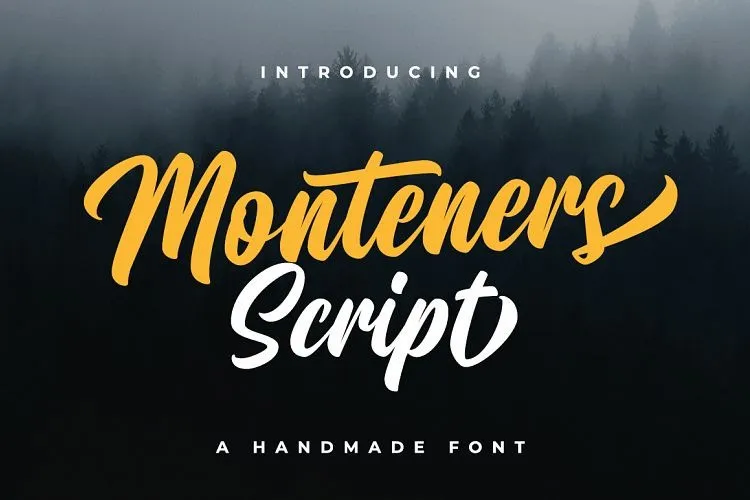
Monteners Script Font – Download Grátis
Estou aqui uma nova fonte Script Bold Retro inspirada em escrita manual, com influência moderna do caligrafismo. Introduzimos a Monteners Font — uma elegante e bonita tipografia script desenvolvida pelo Studio Suby. Esta fonte é perfeita para qualquer projeto gráfico, desde logotipos até posteres, cabeçalhos, cartões personalizados, porcos de mug, camisetas customizadas, e muito mais. A Monteners Font Bold Script é uma escolha ideal para quem deseja adicionar um toque sofisticado a seus projetos. Se você procura uma fonte script com um estilo moderno e elegante, sem dúvida esta será uma opção ótima para você. Descubra por que as pessoas amam a Monteners Font Bold Script e encontre o design perfeito no seu próximo projeto.